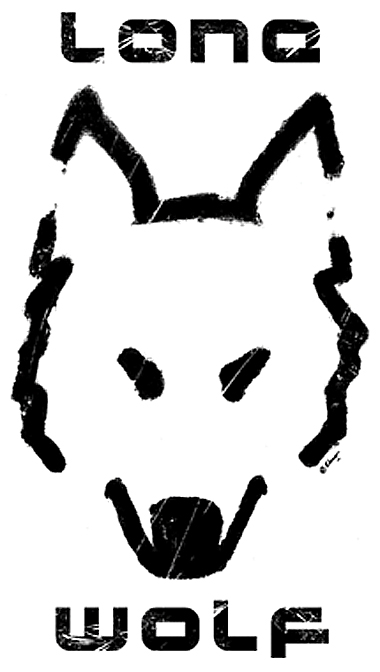
"zenbla min block" was used in the logo of a T-shirt last December.
Minimalista y sofisticado, Buen trabajo!
@DarkoJuan: Estimado compañero en la FS, es verdaderamente muy agradable para mi haber conocido su opinión acerca de mi font "zenbla min block" y además poder leer ese mensaje en español; me gustaría poder seguir recibiendo opiniones en este idioma (mi inglés es francamente mejorable). Translation: @ DarkoJuan: Dear partner in FS, is really very nice for me to have known your opinions about my font "zenbla min block" and also read your message in Spanish, I would like to continue receiving opinions in Spanish (my English is fstrongly improved). Thanks a lot.
@elmoyenique: Compañer@ Fontruccionista, permitame decirle que hay una gran cantidad de diseñadores de hispanoamérica y de gran calidad como usted. en Fontstruct y allá afuera
Very nice! Love your old fonts!
@demonics: Thanks a lot, pal, but all the begginings can be improved, IMHO.
This is brilliant!!! ???
@DecearingEgg: Thank you veeery much for all your kind comments on this and my other fonts that you like. That makes me very happy. And that was the original idea: make fonts usable and people like them. This was one of my first fontstructions and over the years I found several flaws in it, but at that time it served me very well to edit the t-shirts that include it. Thanks again for your interest and keep fontstructing.